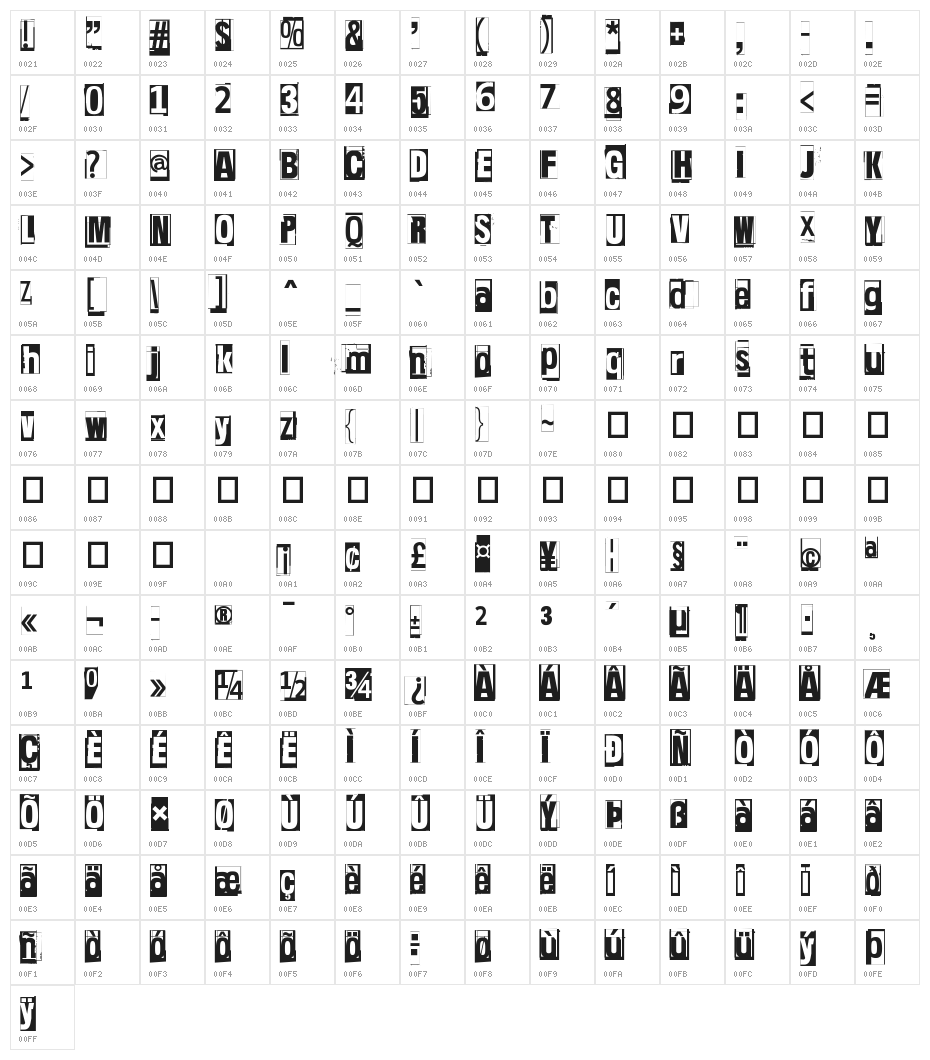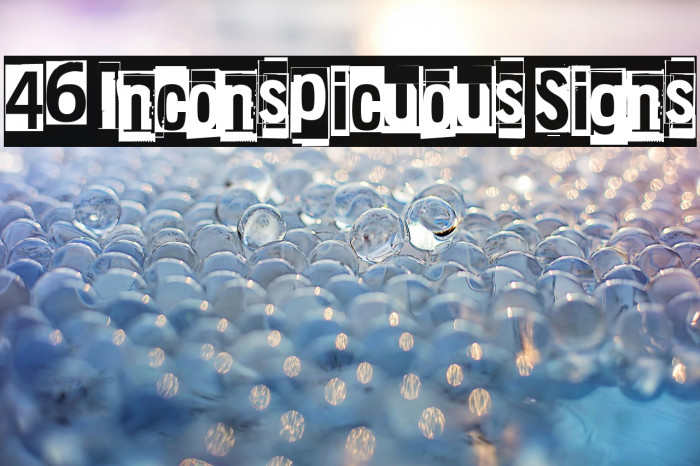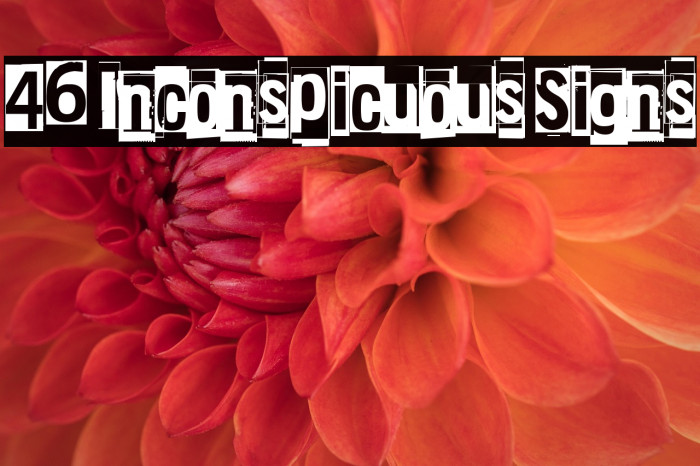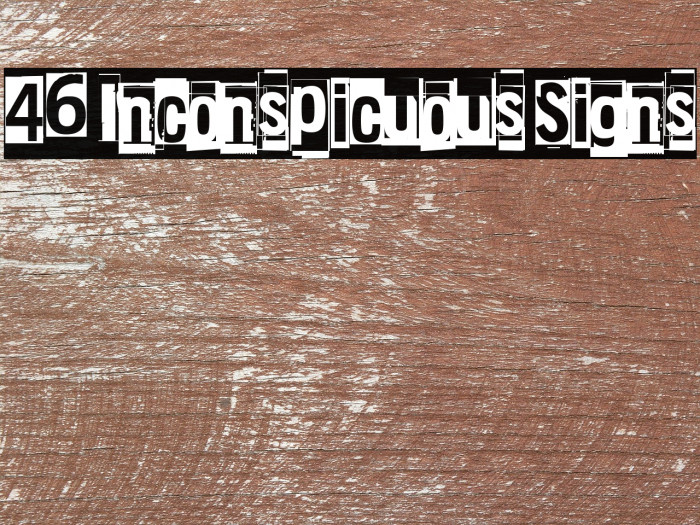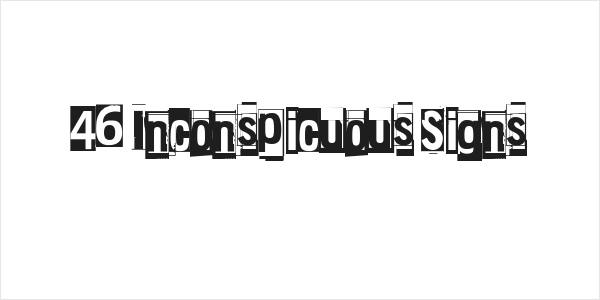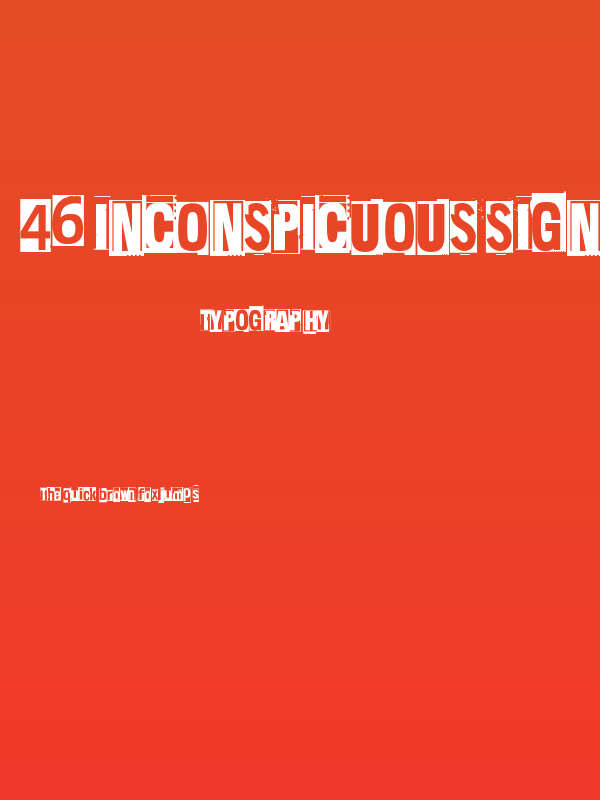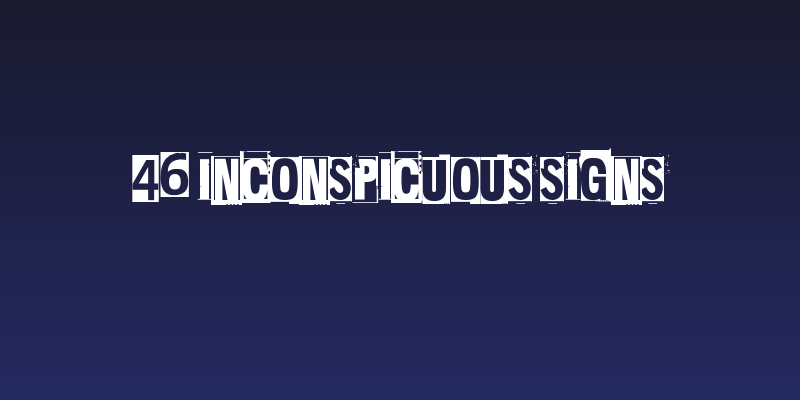
46 Inconspicuous Signs Font
| Stile generale | Grunge, Urban, Edgy |
| Progetti proposti | Ideal for album covers, posters, streetwear branding, and urban-themed designs. |